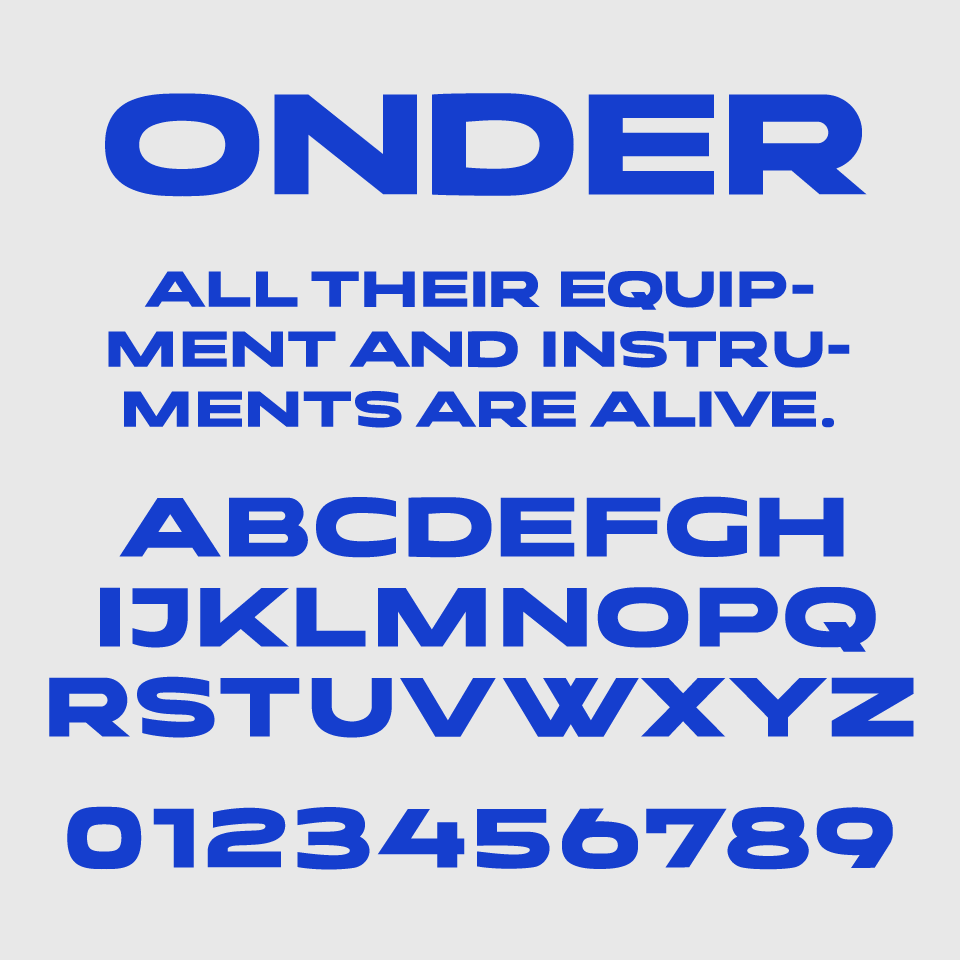
Onderフォントは、エッジの効いた極太ウェイトと、やや広がりのある平体なプロポーションが特徴的なサンセリフフォントです。
直線的な骨格に丸みを加えたデザインは、どこか無機質的な雰囲気で、SFやロボティクス的ななテイストも感じさせます。スローガンやブランド名に用いると、力強く印象に残る効果が期待できます。エネルギッシュでテンションの高いビジュアルを作りたいときにぴったりなフォントです。